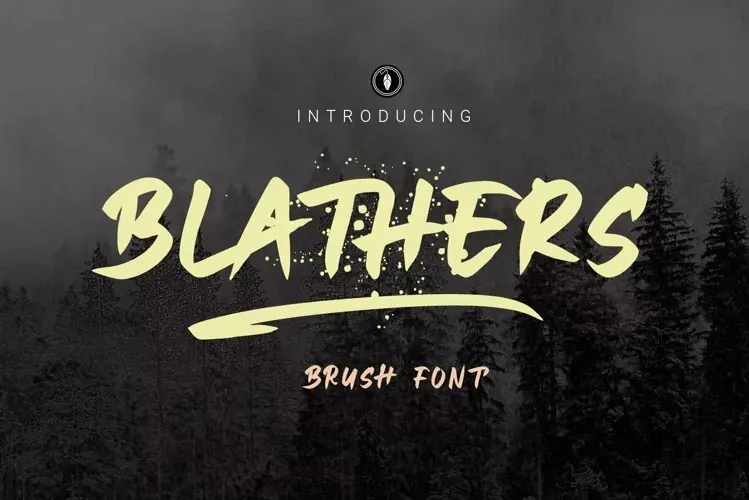
Blathers Font
Este é um pacote de fontes aquareladas criado por Bandofol Studio, conhecido por oferecer um visual cool e despojado. O estilo bold e levemente irracional torna estas fontes ideais para uma ampla variedade de projetos, incluindo logomarcas, identidades corporativas, design de mobiliário, embalagens de produtos, tigelas, frases, outdoors, sacolas de shopping, camisetas, capas de livros, cartões de negócios, convites, carteirinhas de agradecimento, etiquetas, fotografias e marcas especiais. Seu design moderno e elegante o torna perfeito para qualquer projeto que necessite de um toque forte e sofisticado. Blathers Font é uma escolha excelente para quem busca adicionar personalidade ao seu trabalho gráfico. Se você está procurando por fontes aquareladas e bold, Bandofol Studio apresenta Blathers Font como uma opção segura para aumentar o impacto visual de seus projetos, oferecendo um equilíbrio entre simplicidade e originalidade.